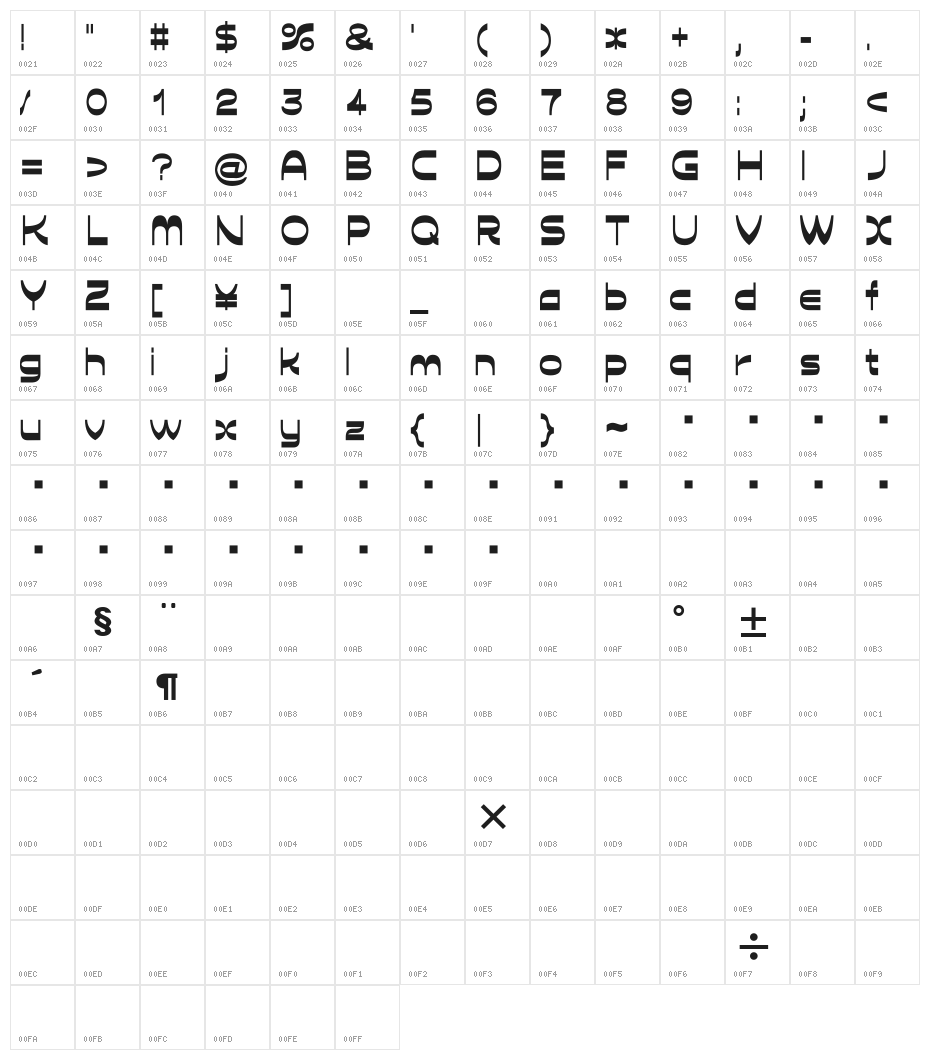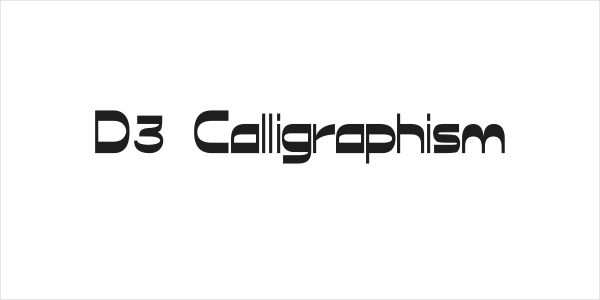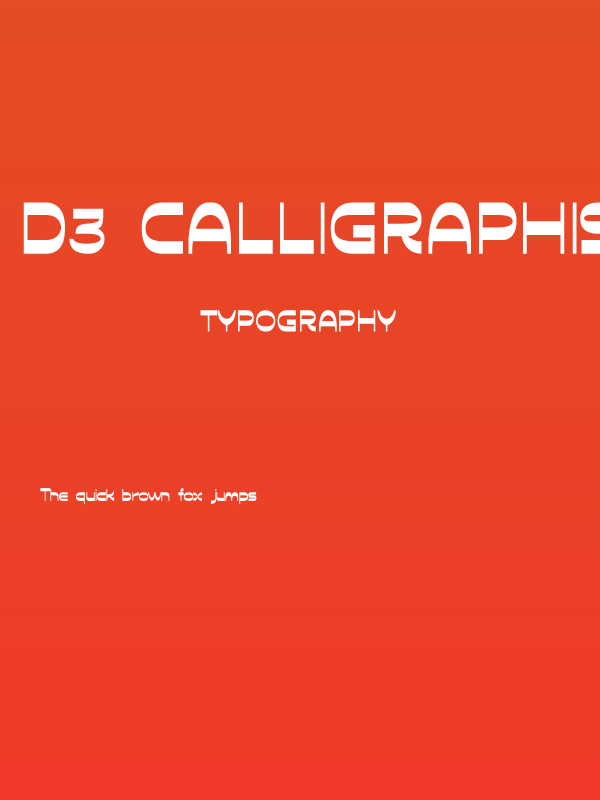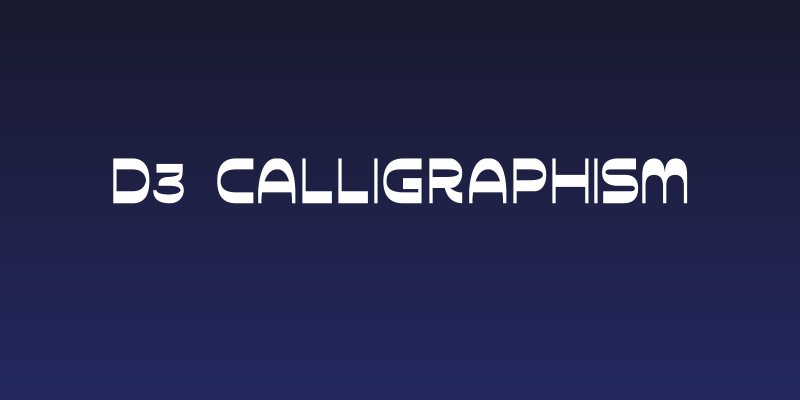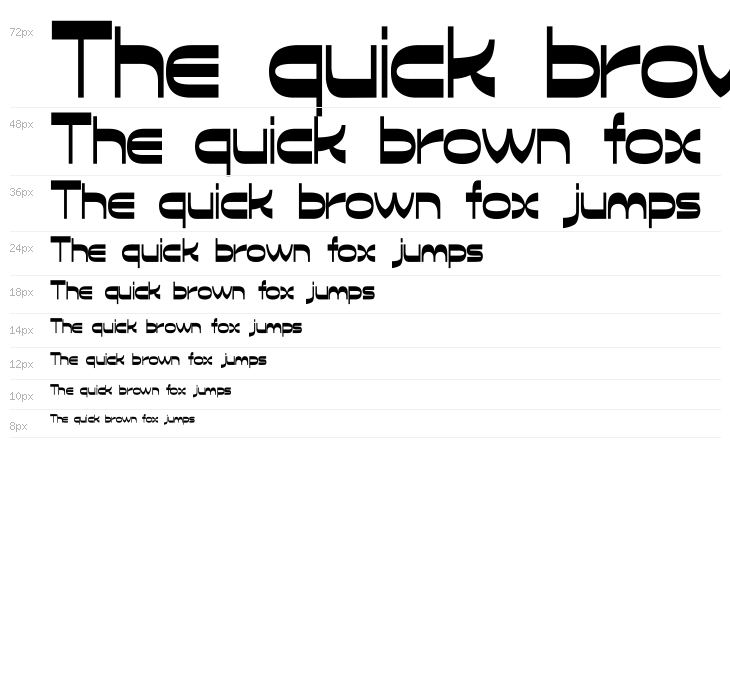
D3 Calligraphism Font
| 分类 | 3D |
| 整体风格 | Futuristic |
| 使用场景 | Headlines, Logos, Branding |
| 推荐项目 | Ideal for branding, advertising, and digital media projects that require a modern and bold aesthetic. |